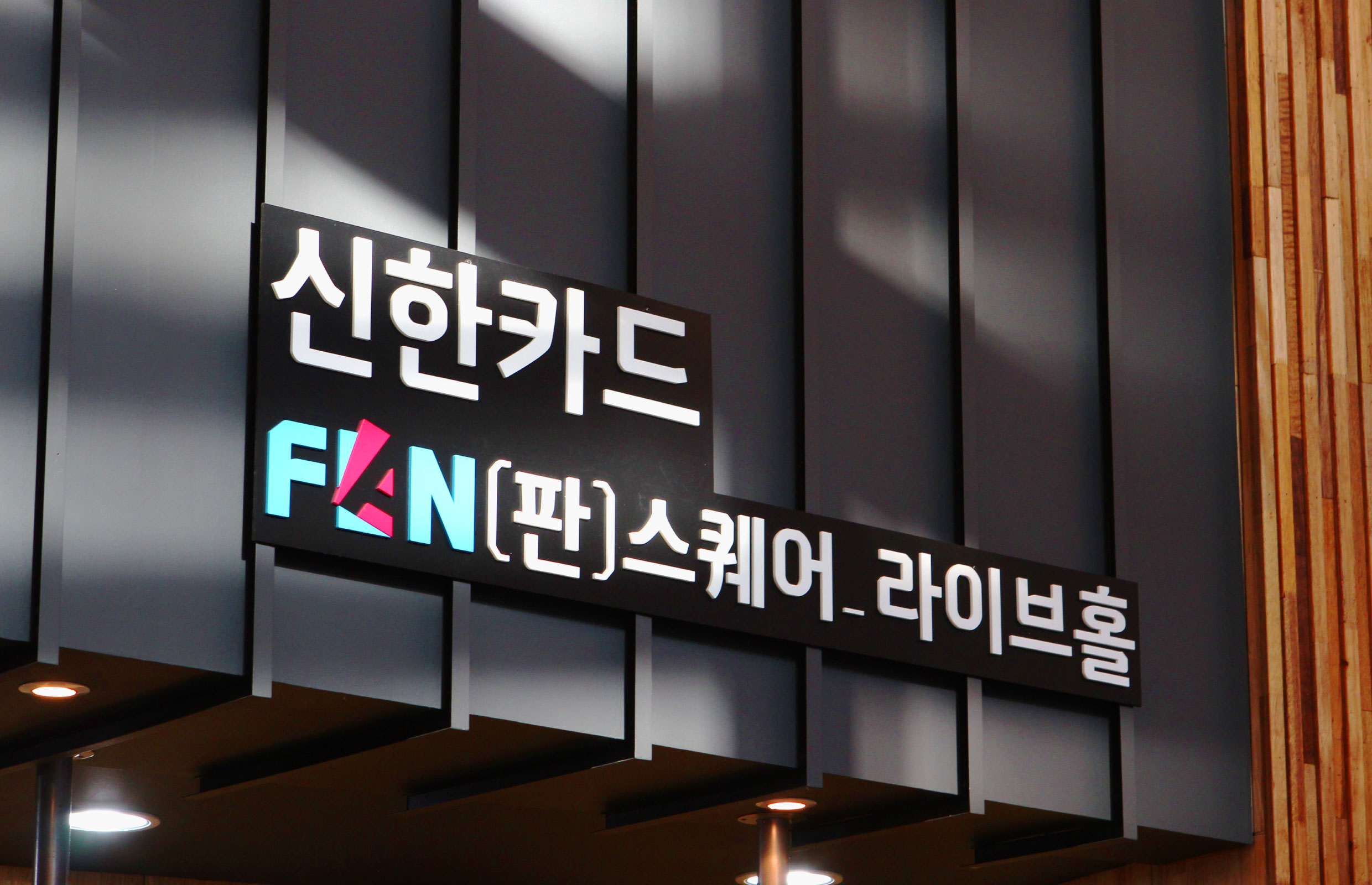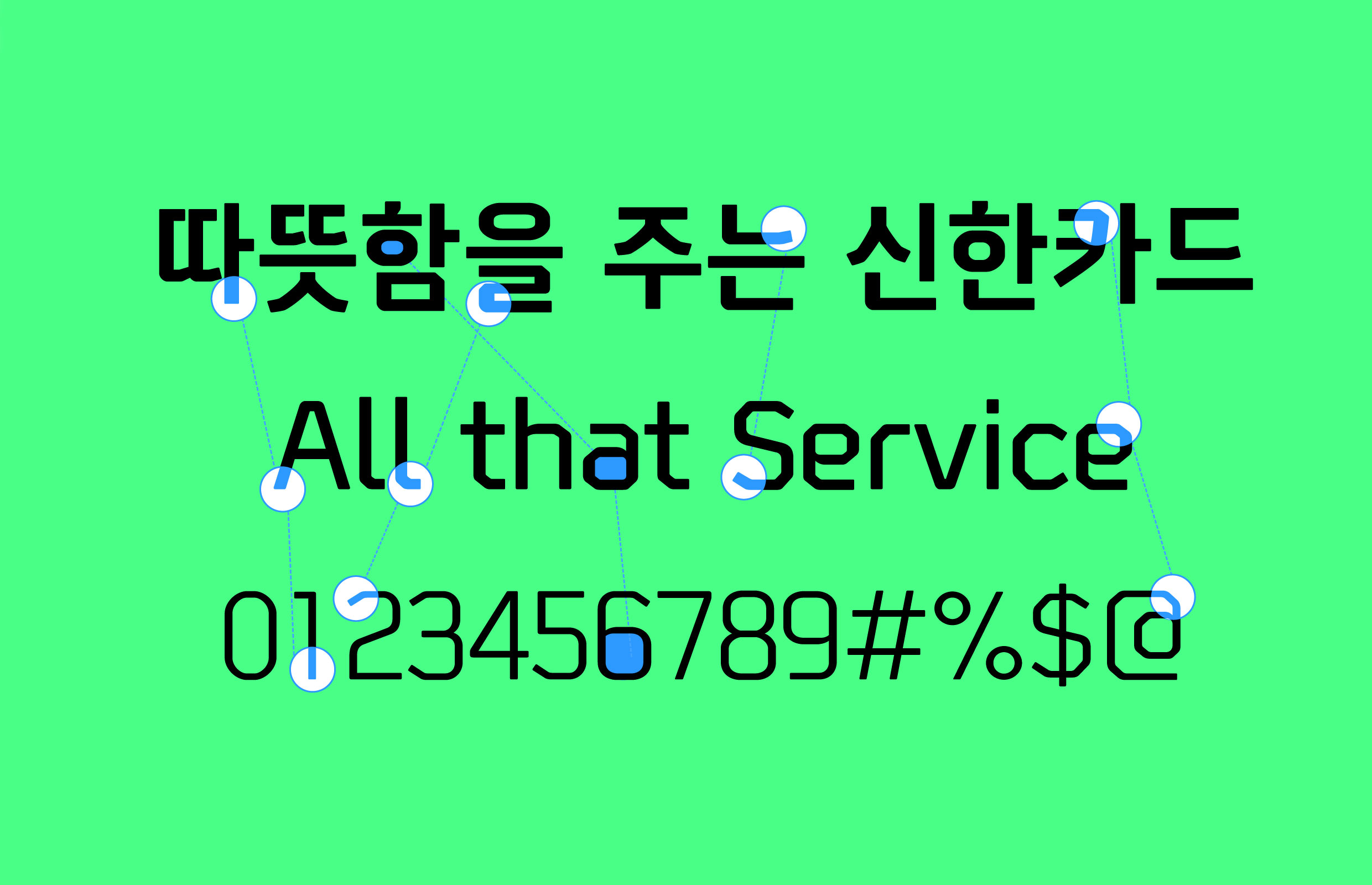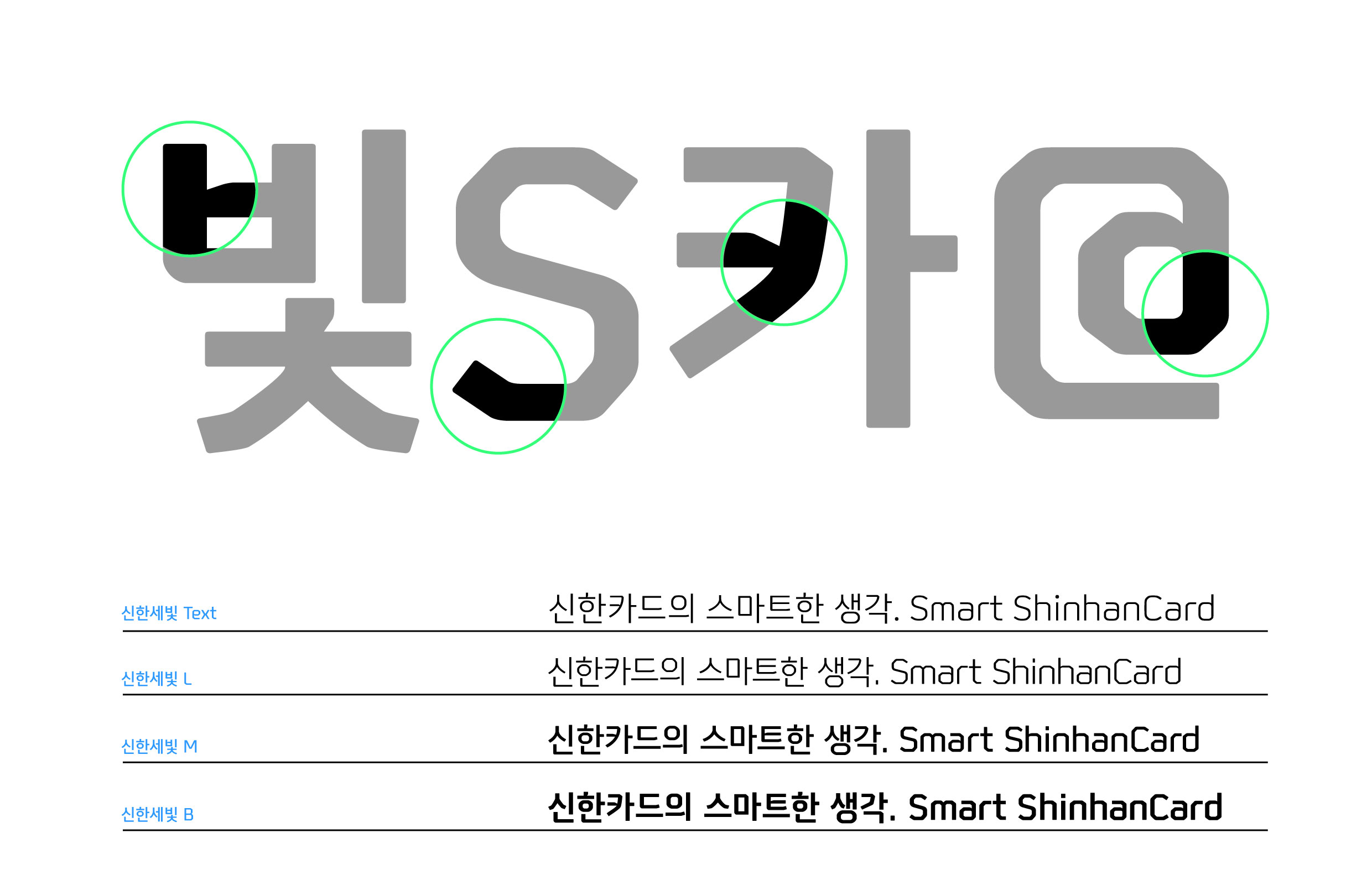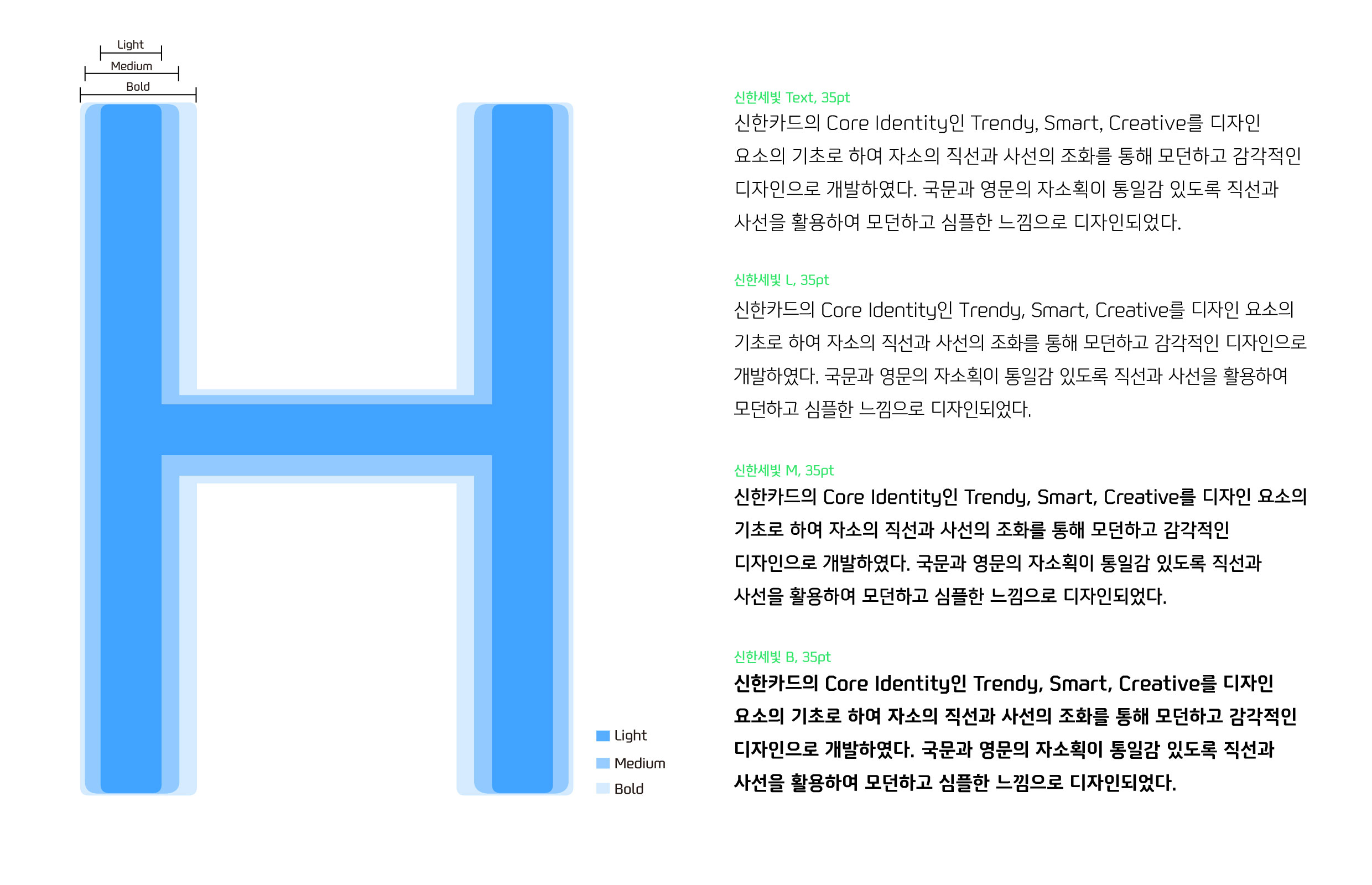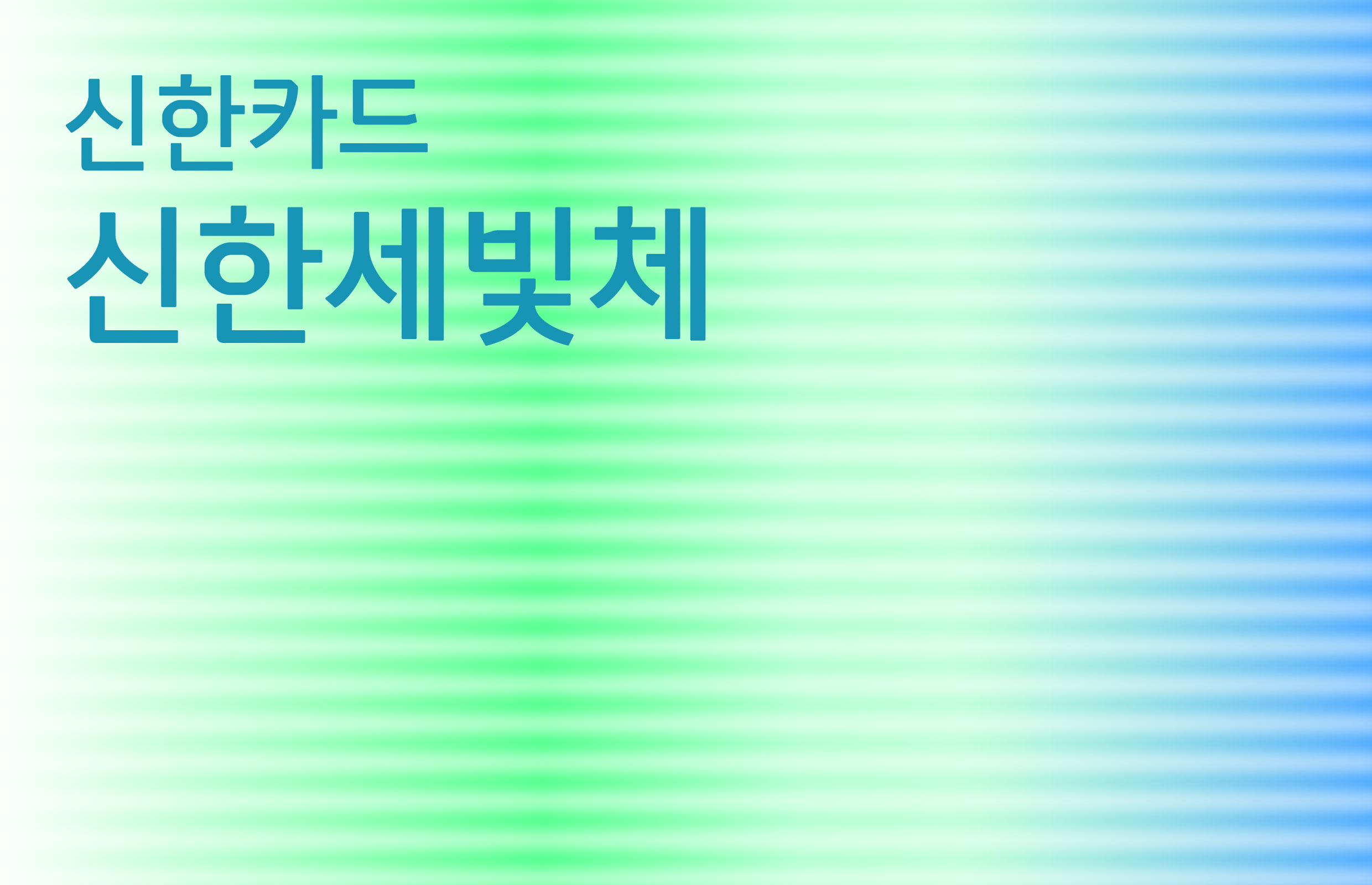
신한카드
신한카드 [신한세빛체]
신한카드의 시각 아이덴티티인 ‘트렌드 스포팅(Trend Spotting)’과 함께 개발된 전용서체. 서체명에 포함된 ‘세빛’은 ‘세상을 밝고 따뜻하게 비춘다’는 의미다. 신한세빛체는 세상에 없던 스포트 라이트(Spot Light)라는 메시지를 내포하여 역동적이고 트렌디한 디자인을 갖추었다.